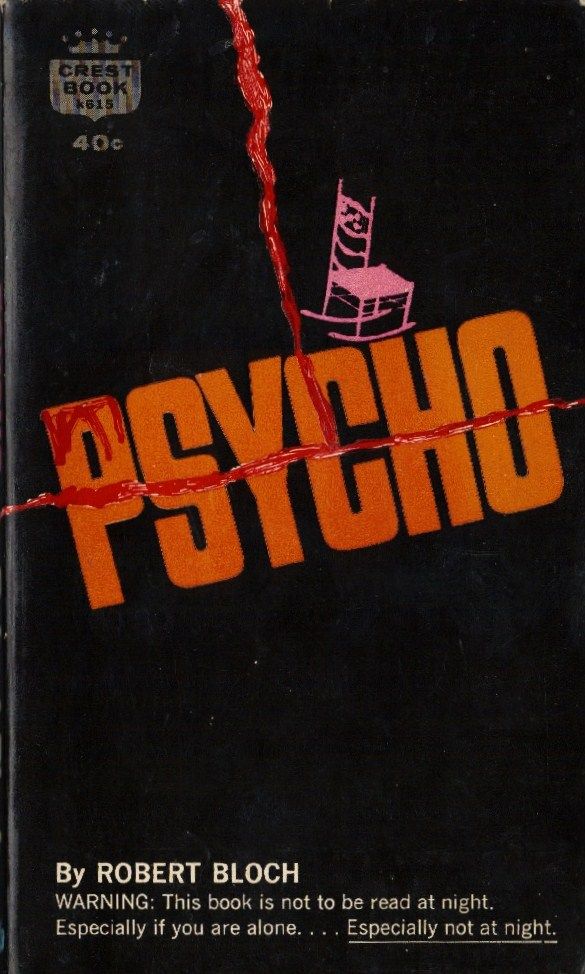
TIPOGRAFÍA DE LA PELÍCULA "PSYCHO"
Alguien podría decirme la tipografía de la película pshyco o una al menos parecida, gracias
Primer resultado de búsqueda en Google:
En la secuencia de los créditos de Saul Bass se utilizan, además, otras dos fuentes: Venus Bold Extended y News Gothic Bold, según narran aquí.
No sé el nombre, pero creo recordar que es creación de Samuel Bass.
Parecidas busca una dentro de las de paloseco.